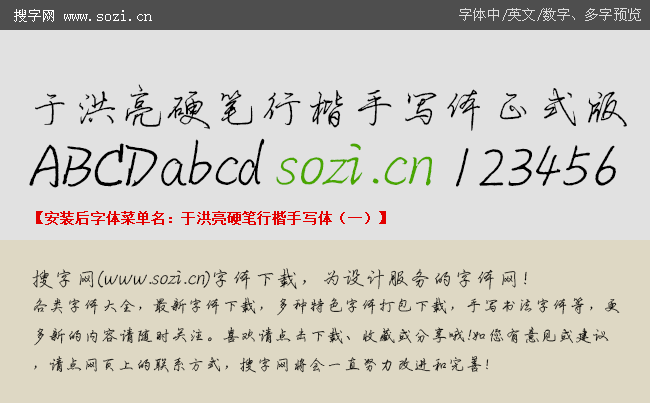
于洪亮硬筆行楷手寫(xiě)體正式版
搜字網(wǎng)提供一款于洪亮硬筆行楷手寫(xiě)體正式版中文書(shū)法字體下載,于洪亮硬筆行楷手寫(xiě)體正式版是一款手寫(xiě)風(fēng)格的鋼筆書(shū)法字體,字體書(shū)寫(xiě)流暢,字形大方,整體效果十分出色,適合應(yīng)用于廣告設(shè)計(jì)、名片設(shè)計(jì)、包裝印刷、產(chǎn)品設(shè)計(jì)等應(yīng)用。